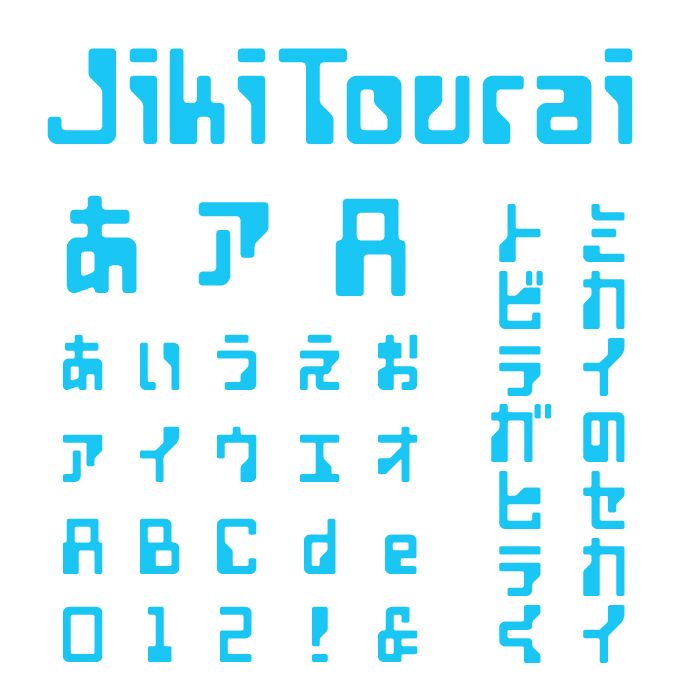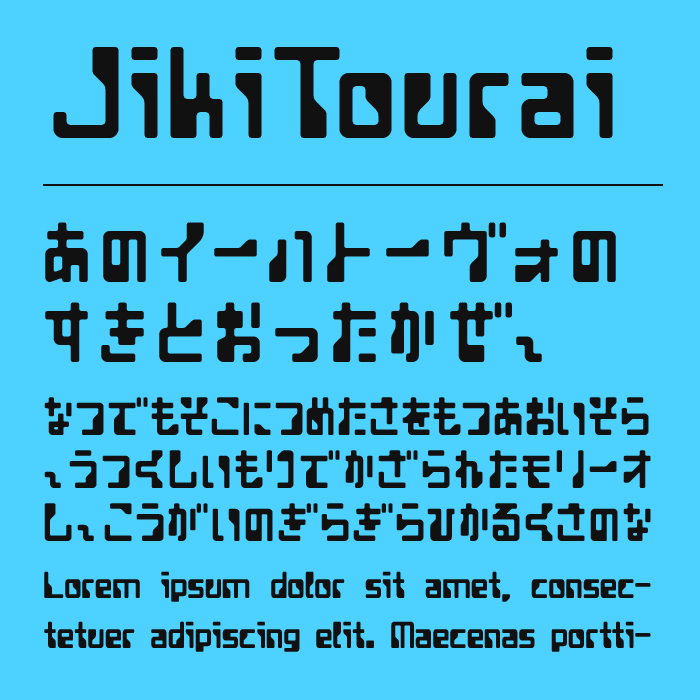
JikiTouraiフォントは、小切手の磁気インクの印字をモチーフにしたデザインかなフォントです。
文字の各パーツが角張っており、情報端末や電子基板を連想させるようなデジタル感があります。角の丸みや装飾をあえて排除したストイックな形状は、SFやメカ系の世界観にぴったりなフォントです。
全体的に視認性は保ちつつ、特有のルールの中で制作されている幾何学的な変形が施されているため、インパクトや目を引くデザインとなっているので、サムネイル、キャッチコピー、タイトルにぴったりです。
収録文字は、ひらがな・カタカナ・アルファベット・数字・記号が収録。